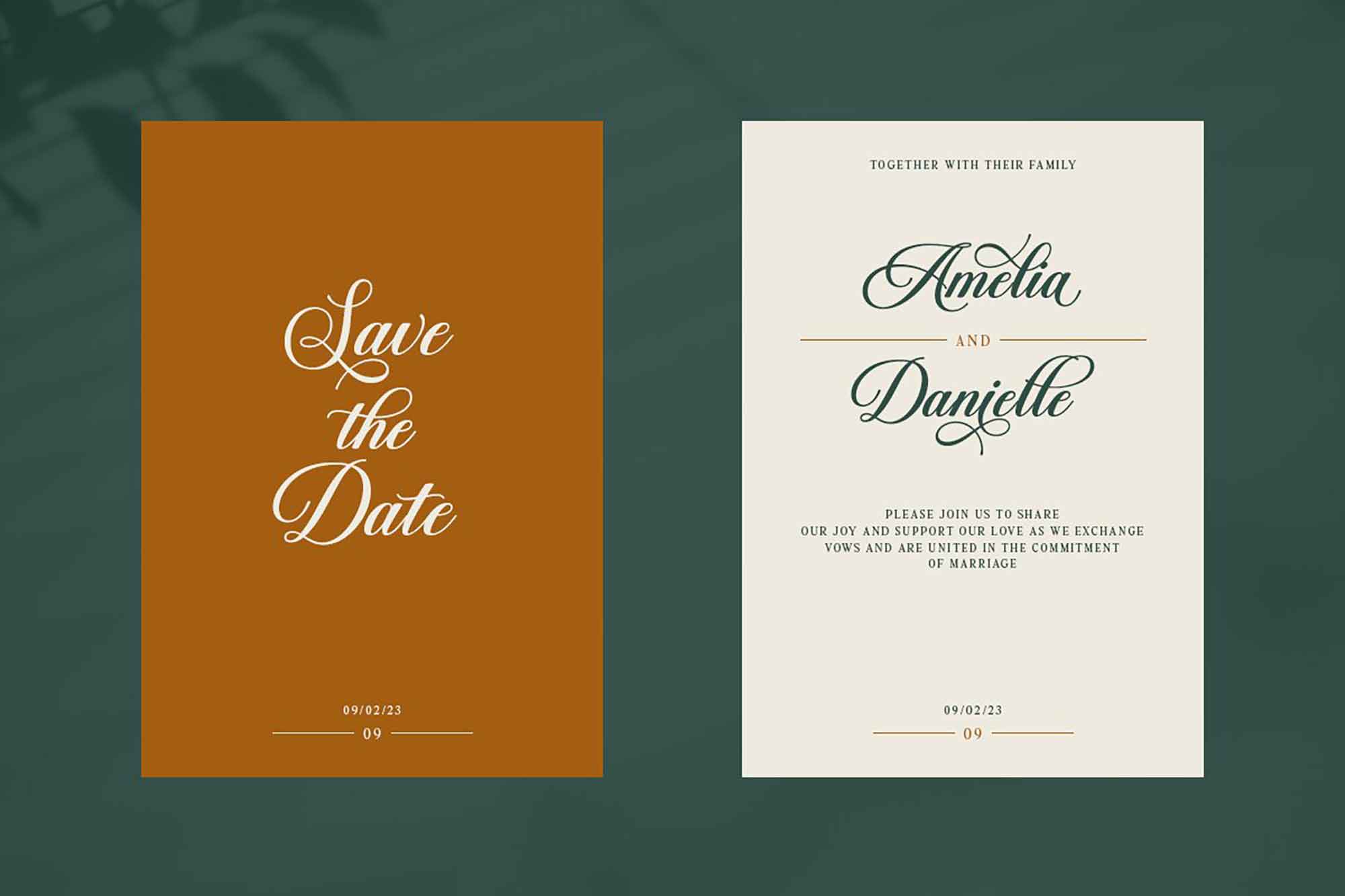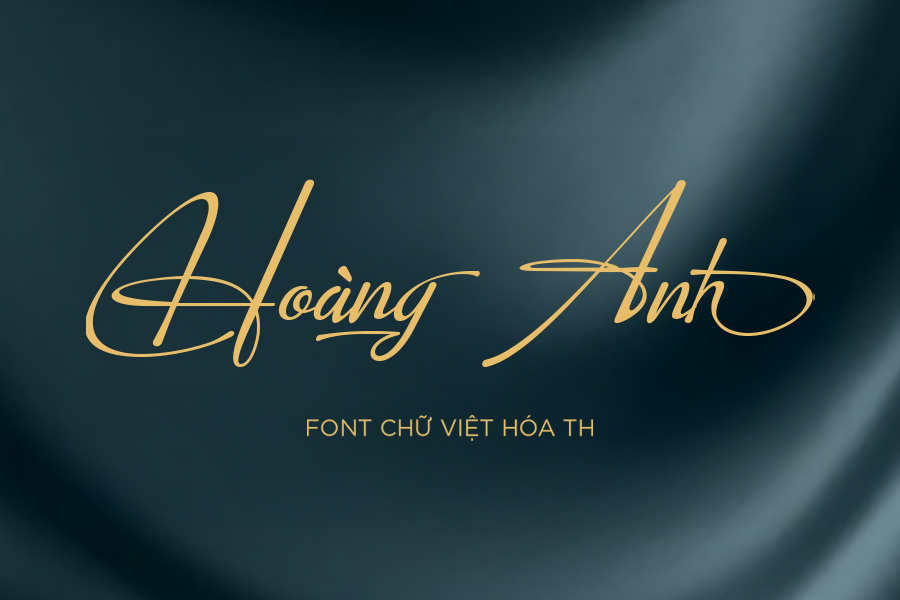
Font chữ mềm mại là nhóm phông chữ có đặc trưng là các đường nét uốn lượn, bay bổng, mô phỏng lại nét bút tay nghệ thuật hoặc phong cách Calligraphy tinh tế. Trong thiết kế đồ họa, những font chữ này được sử dụng như một “vũ khí” để truyền tải sự dịu dàng, sang trọng và nâng cao giá trị thẩm mỹ cho sản phẩm. Doozypack.vn chia sẻ bộ font chữ mềm mại Việt hóa tuyển chọn, hỗ trợ bạn tạo nên những bản thiết kế bao bì mang đậm dấu ấn cá nhân và đầy tính nghệ thuật.
Tại sao font chữ mềm mại lại quan trọng trong thiết kế bao bì?
Lựa chọn kiểu chữ không chỉ để truyền tải thông tin mà còn là cách thương hiệu giao tiếp bằng cảm xúc với khách hàng.
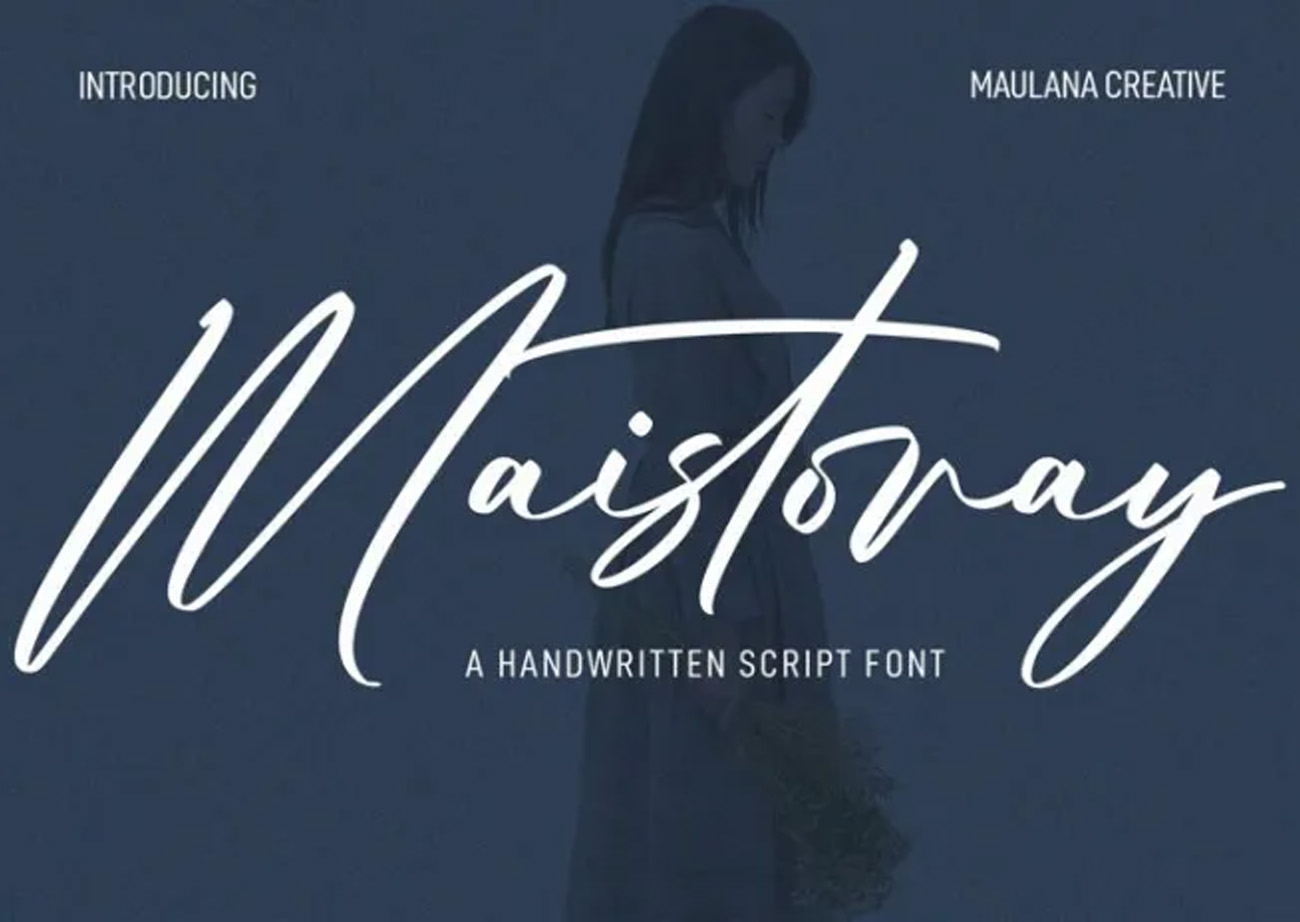
Khơi gợi cảm xúc và sự tinh tế cho sản phẩm
Những đường nét uốn lượn tự nhiên giúp xóa tan vẻ cứng nhắc của các khối bao bì vuông vức. Font chữ mềm mại gợi lên cảm giác về sự chăm chút, tỉ mỉ và nét thủ công tinh xảo. Chính vì thế, các ngành hàng như mỹ phẩm thiên nhiên, trang sức hay quà tặng cao cấp thường ưu tiên nhóm font này để tạo sự kết nối dịu dàng với tâm trí người dùng.
Nâng tầm giá trị thương hiệu sang trọng và đẳng cấp
Một bộ font mềm mại sang trọng có khả năng biến một mẫu túi giấy đơn giản trở thành một tác phẩm nghệ thuật. Sự thanh thoát trong từng nét chữ giúp sản phẩm trông “đắt tiền” và chỉn chu hơn. Khi được kết hợp với các kỹ thuật in ấn hiện đại, font chữ này trở thành điểm nhấn cốt lõi giúp định vị phân khúc cao cấp cho thương hiệu.
Top những bộ font mềm mại sang trọng được Designer săn đón
Dưới đây là một số gợi ý font chữ mềm mại đã Việt hóa được đánh giá cao về tính ứng dụng trong sản xuất thực tế:
- Font Great Vibes: Một bộ font Script chuẩn mực với các đường nét kết nối mượt mà, lý tưởng cho các tiêu đề thiệp cưới hoặc vỏ hộp quà tặng sang trọng.
- Font Dancing Script: Mang phong cách năng động nhưng vẫn vô cùng uyển chuyển, phù hợp cho các thiết kế tem nhãn sản phẩm làm đẹp.
- Font Alex Brush: Sở hữu các nét đưa bút gọn gàng, thanh thoát, giúp văn bản dù mềm mại nhưng vẫn giữ được độ rõ ràng, dễ đọc.
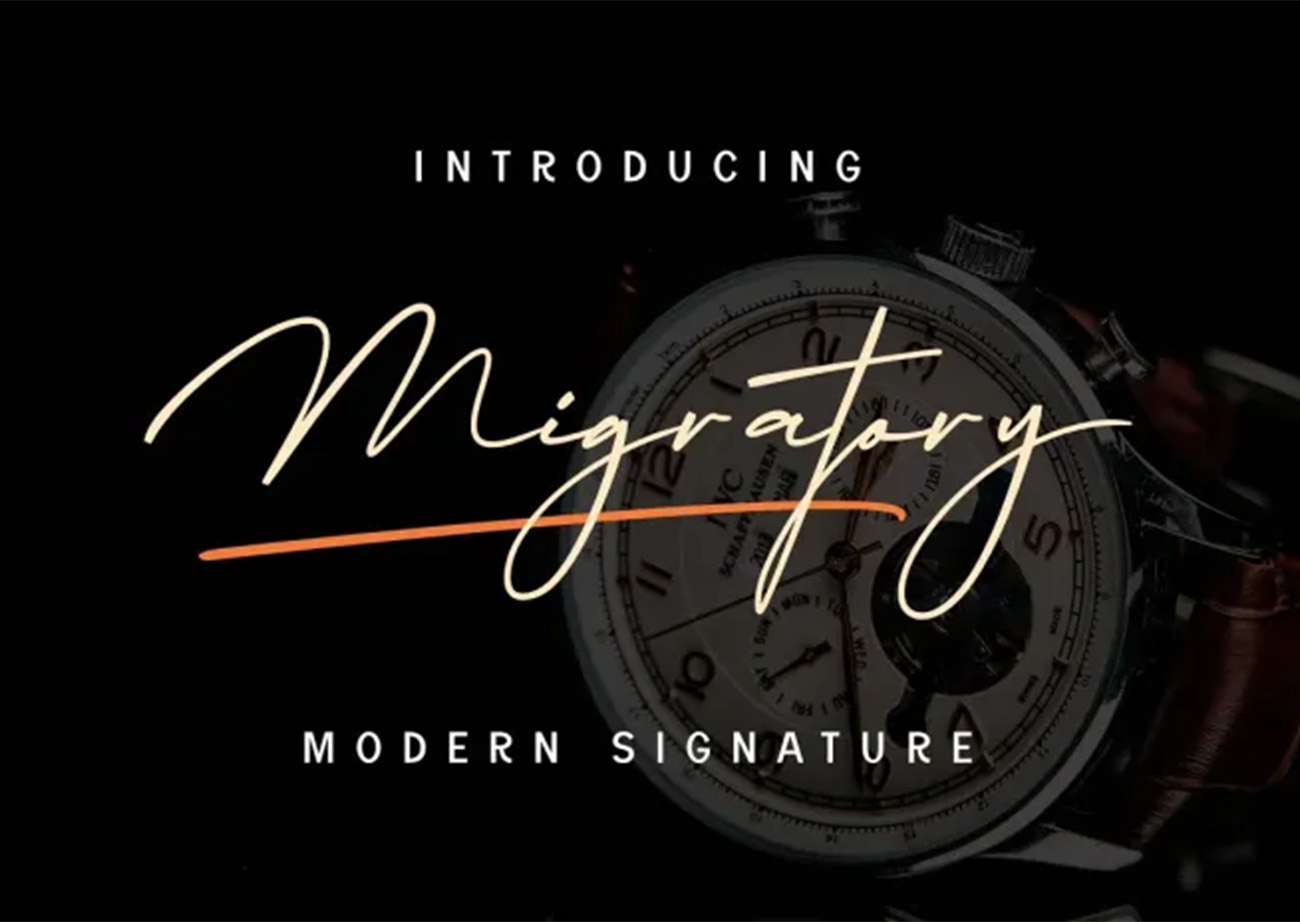
| Phong cách Font | Đặc điểm thị giác | Sản phẩm in ấn phù hợp |
| Calligraphy (Thư pháp) | Cổ điển, quý phái | Thiệp mời, nhãn rượu, vỏ hộp quà tặng cao cấp. |
| Modern Script | Hiện đại, bay bổng | Tem nhãn mỹ phẩm, túi giấy thời trang, banner quảng cáo. |
| Handwriting (Viết tay) | Thân thiện, tự nhiên | Thiệp cảm ơn, bao bì sản phẩm handmade, nhãn đồ uống. |
Lưu ý thiết kế: Font chữ mềm mại phát huy hiệu quả tốt nhất khi được dùng cho tiêu đề chính hoặc các câu slogan ngắn. Bạn nên phối hợp chúng với một font Sans-serif đơn giản cho phần thông tin phụ để bản thiết kế có độ thoáng và chuyên nghiệp hơn.
03 Ứng dụng thực tế của font chữ mềm mại trên bao bì sản phẩm
Việc đưa những nét chữ uốn lượn vào sản xuất thực tế mang lại diện mạo ấn tượng cho sản phẩm khi cầm trên tay:
- Vỏ hộp mỹ phẩm và nước hoa: Một cái tên sản phẩm được thiết kế bằng font mềm mại, ép kim nhũ vàng trên nền giấy mỹ thuật sẫm màu là công thức kinh điển để tạo nên vẻ đẹp đẳng cấp.
- Thiệp cảm ơn đính kèm: Nét chữ viết tay mềm mại giúp thông điệp tri ân của thương hiệu trở nên chân thành và gần gũi hơn với khách hàng.
- Túi giấy in logo: Tên thương hiệu cách điệu theo phong cách mềm mại giúp túi giấy không chỉ là bao bì mà còn là một bộ nhận diện thương hiệu đầy tính thời trang.
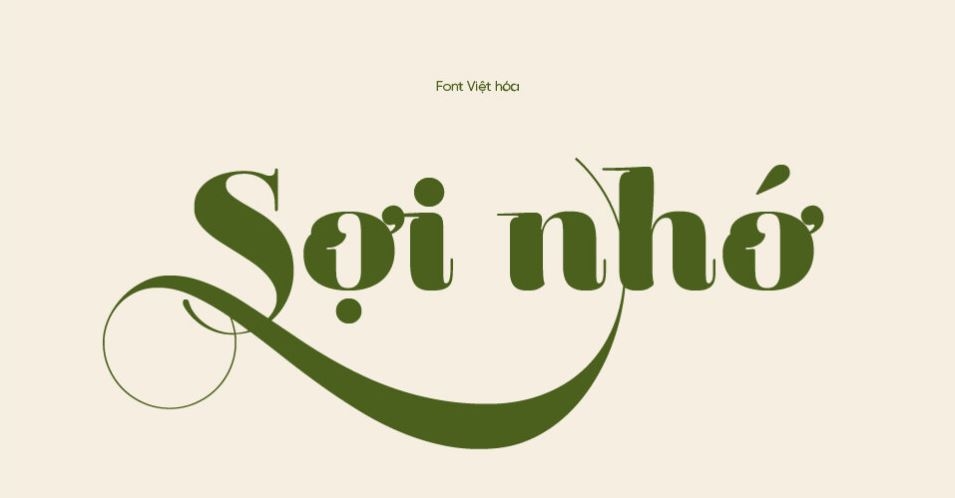
03 Lưu ý kỹ thuật khi in ấn font chữ mềm mại tại Doozypack.vn
In ấn font chữ có nét thanh mảnh yêu cầu sự am hiểu sâu sắc về kỹ thuật sản xuất để tránh các lỗi thường gặp:
- Rủi ro khi ép kim (Foil Stamping): Các nét chữ quá mỏng của font mềm mại có thể bị đứt nét hoặc không bám kim nếu in trên giấy có bề mặt gân sâu. Bạn nên kiểm tra kỹ độ dày nét trong file thiết kế.
- Độ tương phản màu sắc: Trên các chất liệu giấy thấm mực mạnh như giấy Kraft, những nét mảnh dễ bị chìm. Doozypack.vn khuyến nghị bạn nên tăng độ tương phản màu sắc hoặc chọn các style font có nét trung bình để đảm bảo độ sắc nét.